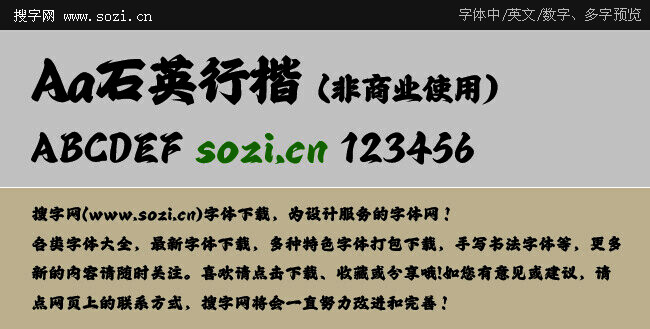
Aa石英行楷
搜字網(wǎng)給大家提供一款A(yù)a石英行楷(非商業(yè)使用)中文字體下載,該字體是一款中文手寫書(shū)法字體,字體筆畫流暢自然,結(jié)構(gòu)肆意灑脫,具有很好的視覺(jué)感。適合圖書(shū)設(shè)計(jì)、包裝設(shè)計(jì)、海報(bào)設(shè)計(jì)等應(yīng)用(此字體為個(gè)人非商用版,商用可以聯(lián)系QQ:1006760504)。